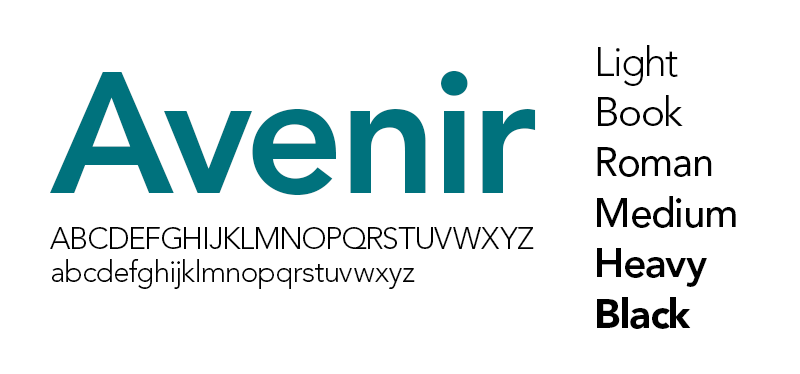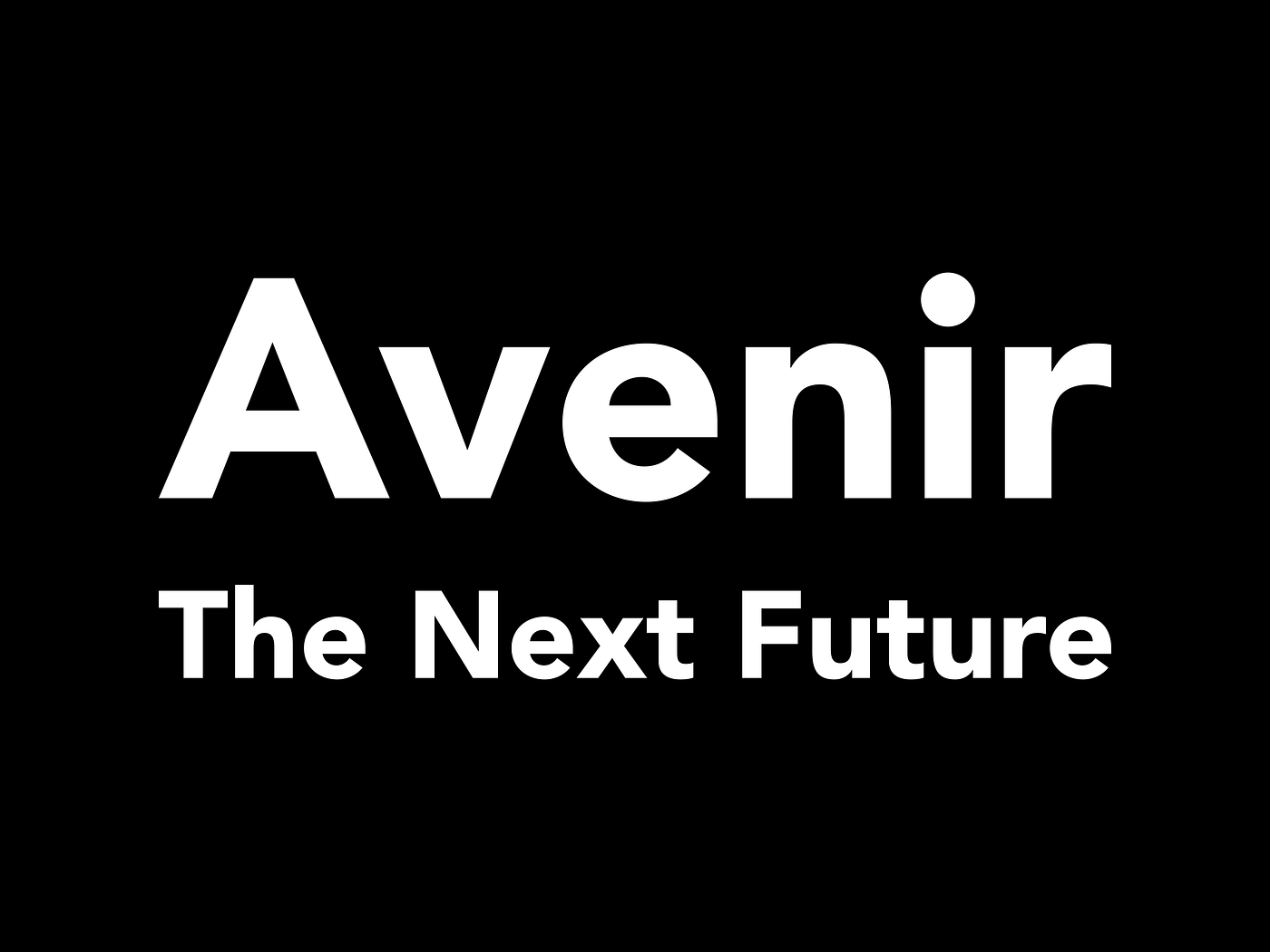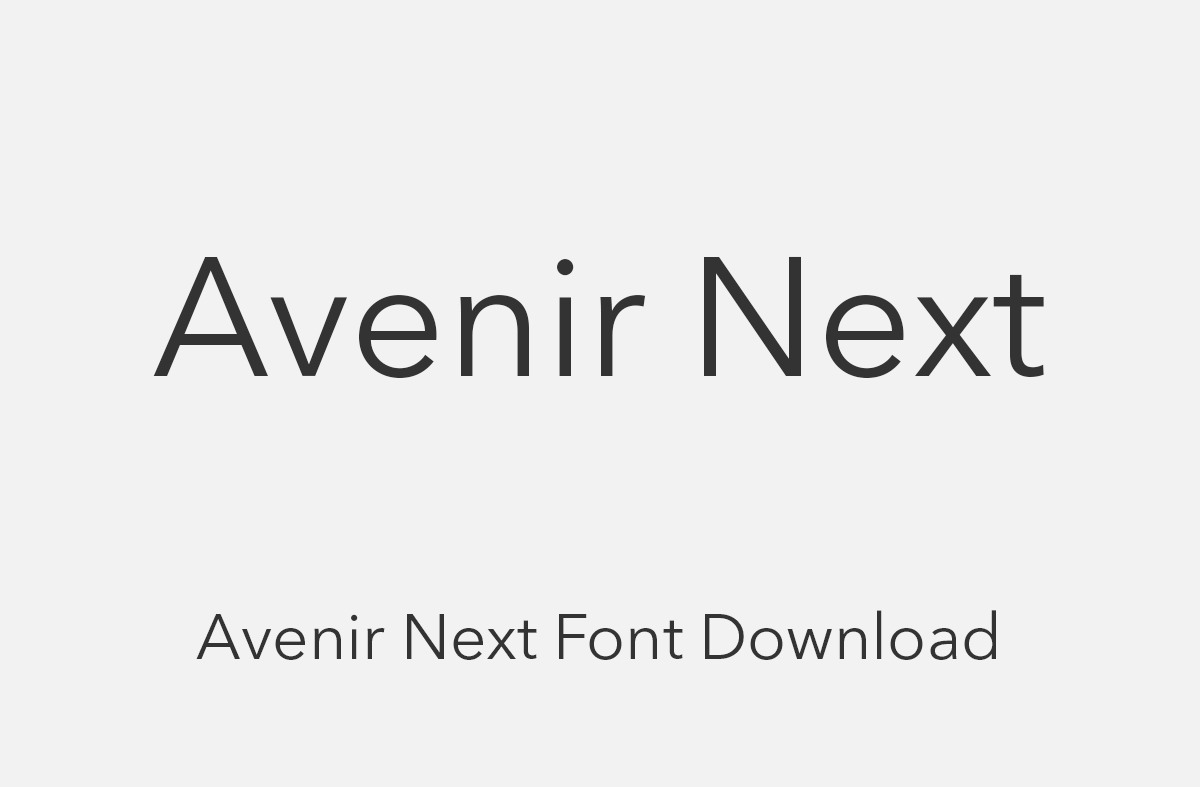
Font Avenir là bộ phông chữ không chân (Sans-serif) kinh điển được thiết kế bởi huyền thoại Adrian Frutiger vào năm 1988. Với cái tên mang ý nghĩa là “Tương lai” trong tiếng Pháp, Avenir được tạo ra nhằm hoàn thiện những khiếm khuyết hình học của Futura, mang lại một diện mạo hiện đại nhưng vô cùng ấm áp và “nhân văn”. Doozypack.vn chia sẻ link download font Avenir trọn bộ, bao gồm các phiên bản Avenir Next Việt hóa chuẩn, giúp bạn sở hữu phông chữ đẳng cấp để thiết kế bao bì và bộ nhận diện thương hiệu chuyên nghiệp mà không lo lỗi dấu.
Đặc điểm thiết kế vượt trội của bộ font Avenir Next
Avenir được giới chuyên môn đánh giá là một trong những bộ phông chữ cân bằng nhất mọi thời đại, là sự giao thoa hoàn hảo giữa hình học chuẩn xác và cảm xúc của nét vẽ tay.
Phong cách Geometric Sans-serif tinh tế
Đặc trưng lớn nhất của Avenir font là cấu trúc chữ dựa trên các hình khối cơ bản nhưng được tinh chỉnh tỉ mỉ. Khác với các dòng font hình học cứng nhắc, Avenir có các nét dọc dày hơn nét ngang một chút, giúp mắt người nhận diện mặt chữ tự nhiên và dễ dàng hơn. Thiết kế này mang lại cảm giác minh bạch, trung tính nhưng vẫn rất sang trọng, cực kỳ phù hợp cho các thương hiệu thời trang cao cấp và startup công nghệ.
Sự phát triển mạnh mẽ của Avenir Next
Font Avenir Next là phiên bản nâng cấp toàn diện được Akira Kobayashi và Adrian Frutiger thực hiện để tối ưu hóa cho kỷ nguyên kỹ thuật số. Phiên bản này mở rộng hệ thống độ dày nét (Weights) và bổ sung các biến thể Avenir Next Condensed font (cấu trúc hẹp). Điều này giúp designer có sự linh hoạt tuyệt đối trong việc dàn trang bao bì, từ những tiêu đề lớn mạnh mẽ đến những dòng chú thích nhỏ sắc nét.
Tại sao designer nên tải font Avenir Việt hóa cho thiết kế bao bì?
Trong ngành sản xuất bao bì tại Doozypack.vn, Avenir luôn nằm trong danh mục các font chữ “quyền lực” nhất nhờ những ưu điểm vượt trội:
- Hoàn thiện nội dung tiếng Việt: Việc sử dụng bản Avenir font việt hóa chuẩn đảm bảo các dấu thanh (sắc, huyền, hỏi, ngã, nặng) được đặt ở vị trí cân đối, hài hòa với cấu trúc chữ, không gây hiện tượng lỗi font hay dấu bị đè nét.
- Tạo dấu ấn Luxury: Avenir mang lại diện mạo “Premium” ngay lập tức cho vỏ hộp, giúp thương hiệu dễ dàng chinh phục phân khúc khách hàng cao cấp.
- Độ hiển thị xuất sắc ở kích thước nhỏ: Nhờ khoảng hở trong chữ (counter) thoáng đãng, các thông tin bảng thành phần trên nhãn dán vẫn cực kỳ rõ nét khi in bằng font Avenir.
| Biến thể Font | Đặc điểm thị giác | Ứng dụng đề xuất tại Doozypack.vn |
| Avenir Book / Regular | Thanh thoát, dễ đọc | Dùng cho nội dung hướng dẫn sử dụng, bảng thành phần (Body text). |
| Avenir Bold / Black | Vững chãi, nổi bật | Dùng làm tiêu đề chính, tên sản phẩm hoặc logo thương hiệu. |
| Avenir Next Condensed | Hẹp, tiết kiệm diện tích | Dùng cho các mặt bên của hộp giấy hoặc tem nhãn diện tích nhỏ. |
Tư vấn từ chuyên gia: Nếu bạn thiết kế bao bì mỹ phẩm tối giản, hãy thử kết hợp Avenir black font download cho tên thương hiệu và Avenir Light cho thông tin công dụng. Sự tương phản này sẽ tạo nên một diện mạo vô cùng chuyên nghiệp và hiện đại.
03 Ứng dụng của font Avenir trong sản xuất bao bì thực tế
Sự hiện đại và minh bạch của font Avenir Next Việt hóa mang lại hiệu quả thị giác đặc biệt trên các ấn phẩm tại Doozypack.vn:
- Hộp mỹ phẩm & Nước hoa: Nét chữ hình học tinh tế của Avenir cực kỳ đồng bộ với phong cách thiết kế Minimalism, tạo nên vẻ đẹp thuần khiết cho vỏ hộp.
- Túi giấy doanh nghiệp: Tên công ty in bằng Avenir Bold trên túi giấy Ivory cán màng mờ tạo cảm giác uy tín và vững chắc cho thương hiệu.
- Tem nhãn dán thông minh: Cấu trúc rõ ràng giúp các bảng thông số kỹ thuật trên tem decal trở nên dễ tra cứu và thẩm mỹ hơn cho người tiêu dùng.
03 Lưu ý kỹ thuật khi in ấn với phông chữ Avenir
Sản xuất bao bì sử dụng phông chữ đặc thù như Avenir đòi hỏi designer cần lưu ý một số vấn đề kỹ thuật tại xưởng in chuyên nghiệp:
- Kiểm soát độ tràn mực (Dot Gain): Các khe hở trong chữ của Avenir khá thoáng nên rất an toàn khi in Offset. Tuy nhiên, trên giấy Kraft thô nhám, bạn nên để size chữ tối thiểu từ 6pt trở lên.